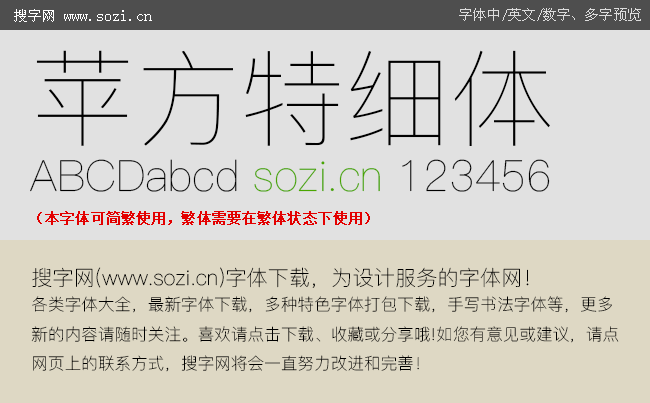
蘋方特細(xì)體
搜字網(wǎng)提供一款蘋方特細(xì)體中文字體下載,蘋方字體是蘋果為其新版中文系統(tǒng)全新設(shè)計(jì)的字體,該字體具有現(xiàn)代感的外觀和清晰易讀的效果,可用于報(bào)刊雜志排版,也適用于平面廣告,圖書印刷等廣告設(shè)計(jì)場(chǎng)合使用。
• 風(fēng)格類別: 線體